영문·한글 혼용 폰트가 어긋나 보이는 패턴 — 실패에서 역산한 페어링 원칙
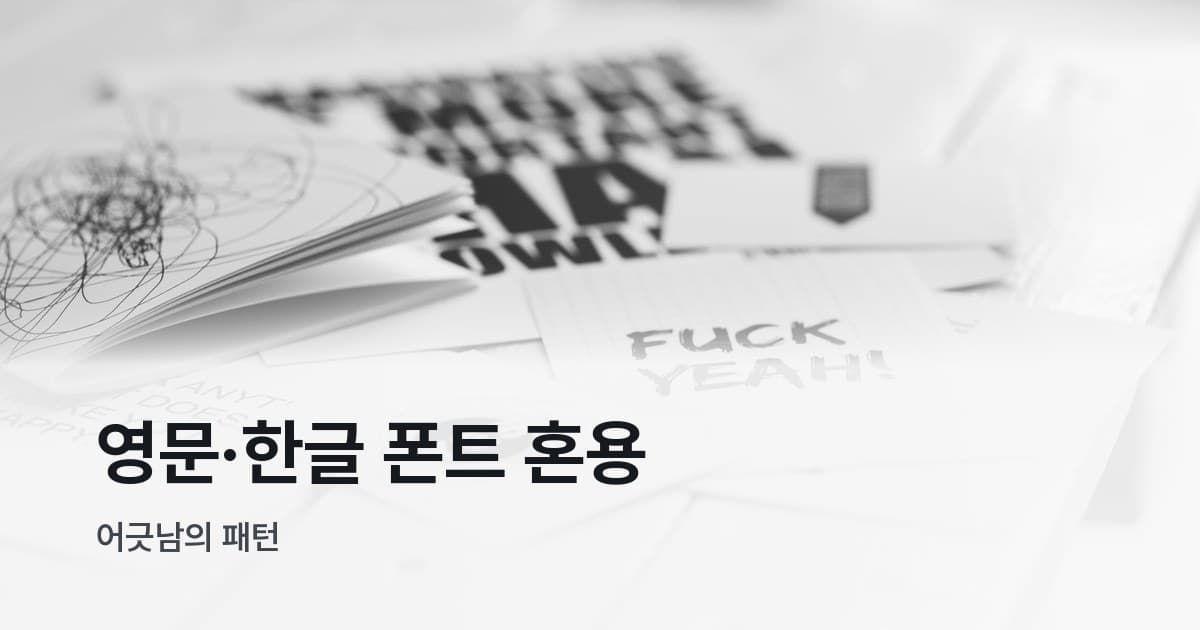
디자인 파일을 열어두고 한 시간째 폰트 조합을 바꿔보는 상황을 한 번쯤 겪어봤을 거예요. 영문 폰트도 예쁘고, 한글 폰트도 마음에 드는데 — 막상 둘을 나란히 놓으면 뭔가 엇나간 느낌. 크기를 올려봐도, 자간을 조정해봐도 여전히 찜찜하다. 결국 시간에 쫓겨 "그냥 Noto Sans로 퉁치자"고 타협했다면, 그 실패는 감각 부족 때문이 아니에요.
어색한 결과물에서 거꾸로 올라가 보면, 원인은 거의 세 가지 중 하나에 걸립니다. x-height 불일치, 굵기 밀도 미스매치, 그리고 분위기 충돌. 이 글은 "잘 어울리는 조합 목록"을 나열하는 대신 — 실제로 무너지는 지점부터 먼저 짚고, 그 원인을 거꾸로 설명합니다. 실패가 어디서 오는지 알면 처음 보는 폰트 조합도 스스로 판단할 수 있거든요.
결과물이 어색하다면 x-height 불일치부터 의심하라
x-height는 라틴 소문자 'x'의 높이, 즉 소문자가 실제로 차지하는 세로 공간이에요. 같은 16px라도 x-height가 큰 폰트는 꽉 찬 느낌을 주고, x-height가 낮은 폰트는 같은 크기에서 훨씬 가냘프게 보입니다.
문제는 한글과 영문이 서로 완전히 다른 설계 체계에서 출발한다는 점이에요. 한글은 정사각형에 가까운 고정폭 공간 안에 자모가 배치되는 구조라, 영문 소문자의 어센더·디센더 개념 자체가 없어요. 그래서 두 폰트를 같은 포인트로 나란히 놓으면 높이 기준이 어긋나 — 한글이 지나치게 크거나, 영문이 유독 작아 보이는 현상이 생깁니다.
Pretendard가 Inter와 잘 어울리는 이유가 여기에 있어요. Pretendard는 라틴 글리프를 Inter에서 가져와 한글(본고딕 계열)과 조합해, 같은 환경에서 x-height가 자연스럽게 통일되도록 설계됐거든요. Google Fonts Knowledge에서도 x-height를 서로 다른 폰트를 혼용할 때 시각적 균형에서 가장 먼저 확인해야 할 기준으로 꼽습니다. 반면, x-height가 유독 낮은 클래식 세리프 영문 폰트에 고밀도 한글 폰트를 그냥 붙이면 — 한글이 영문보다 눈에 띄게 크고 무거워 보이는 결과가 나와요.
같은 Regular인데 한글만 더 진해 보이는 굵기 밀도 미스
"둘 다 Regular니까 균형은 맞겠지."
근데 한글 쪽이 확연히 더 어둡게 보이면, 내 모니터가 이상한 걸까요? 아니에요.
한글은 자모 획이 영문 알파벳보다 훨씬 많고, 정사각형 공간 안에 빽빽하게 들어갑니다. 획 굵기 자체는 같아도 페이지 위에서 더 어둡고 조밀하게 느껴질 수밖에 없는 구조예요. 이건 폰트 품질의 문제가 아니라 한글이라는 문자 체계 자체의 특성입니다.
그래서 실무 보정 방향은 간단해요. 영문 Light + 한글 Light 조합에서 한글이 확연히 진해 보인다면, 영문만 Regular로 올리거나 한글 font-weight를 한 단계 내리는 거예요. 반대로 처음부터 이 문제를 피하고 싶다면, 같은 패밀리 안에서 라틴과 CJK를 함께 설계한 폰트를 고르면 됩니다. Noto Sans와 Noto Sans KR이 그 사례예요 — 같은 프로젝트에서 명도를 맞추도록 만들어졌기 때문에 같은 weight로 써도 비교적 잘 맞거든요.
이 문제가 가장 두드러지게 나타나는 조합이 Light·Thin 계열 영문과 Regular 한글을 섞을 때예요. 영문을 가늘게 써서 세련된 느낌을 내려다가, 옆에 붙은 한글이 지나치게 무겁게 보여서 결국 전체적으로 불균형한 결과가 나오는 경우입니다. 이 경우는 한글도 Light로 낮추는 것보다 — 두 폰트 모두 Regular 이상에서 시작하고 무게를 함께 조정하는 편이 더 안정적인 결과를 줘요.
수치는 다 맞는데도 글자가 싸우는 느낌, 분위기 충돌
글자 크기와 굵기 밀도가 잘 맞더라도 분위기가 충돌하면 조합은 깨집니다.
Playfair Display는 획 굵기 대비가 강한 고전 세리프 서체예요. 고급스럽고 우아한 인상을 주는 폰트죠. 여기에 획 굵기가 균일하고 현대적인 Noto Sans KR을 붙이면 — 영문과 한글이 서로 다른 시대에서 온 듯한 이질감이 생겨요. 글자가 싸우는 느낌이랄까요.
Adobe Fonts의 다국어 조판 가이드에서도 감성적 어울림을 먼저 살피고 수치를 나중에 조정하도록 안내합니다. 세리프 영문에는 세리프 한글(본명조, Noto Serif KR)을, 산세리프 영문에는 산세리프 한글(고딕 계열)을 기본으로 가져가는 게 출발점이에요. 세리프·산세리프를 의도적으로 섞는 경우도 있지만, 그건 충분한 크기 대비와 역할 분리(제목용/본문용)가 뒷받침될 때만 성립합니다.
안전한 조합에서 공통점을 역산하면
아래는 영문 폰트와 한글 폰트의 조합을 x-height·굵기·분위기 세 기준에서 왜 어울리는지 정리한 것입니다. 목록보다 근거 쪽에 주목해 보세요 — 이 표의 진짜 목적은 조합 암기가 아니라, "왜 되는지"를 역산하는 데 있어요.
| 영문 폰트 | 한글 폰트 | 어울리는 근거 |
|---|---|---|
| Inter | Pretendard | Pretendard가 Inter의 라틴 글리프를 가져와 한글과 조합 — 같은 환경에서 x-height 자연 통일 |
| Noto Sans | Noto Sans KR | 같은 Noto 프로젝트에서 라틴·CJK 명도 통일 설계 |
| Playfair Display | 본명조 (Source Han Serif) | 획 대비 있는 세리프 계열 — 분위기 일치 |
| Georgia | Noto Serif KR | 중간 세리프 명조 계열 — 웹 가독성·분위기 일치 |
| Roboto | Noto Sans KR | Google 산하 산세리프 계열 — 굵기·간격 기준 정렬 |
이 표에서 공통점을 역산하면 세 가지예요. 같은 프로젝트에서 함께 설계됐거나, 같은 세리프/산세리프 계열이거나, 수직 메트릭을 참고해 맞추도록 만들어진 경우. 이 세 조건 중 하나라도 해당하면 일단 안전한 조합이에요.
어색함이 느껴졌을 때 어디서 무너졌는지 역산하는 법 🔍
"이미 써봤는데 어색해" — 이 상태에서 시작하는 역산 흐름입니다. 위에서 짚은 세 가지 실패 원인을 기준으로, 느껴지는 증상에서 거꾸로 올라가면 원인을 찾을 수 있어요.
증상: 한글과 영문의 시각적 크기가 다르게 느껴진다
포인트는 같게 설정했는데도 한글이 유독 크거나 영문이 왜소해 보인다면 x-height 문제예요. 두 폰트를 같은 크기로 나란히 놓고 라틴 소문자 높이를 기준으로 비교해 보세요. 차이가 눈에 띄게 크다면 — 폰트 자체를 바꾸거나, 시각적으로 작아 보일 수 있어 한글 쪽 font-size를 살짝 낮추는 경우도 있습니다. Pretendard + Inter처럼 수직 메트릭을 맞춰 설계된 쌍을 쓰면 이 문제 자체가 발생하지 않아요.
증상: 한글만 확연히 어두워 보인다 (같은 Regular인데)
이건 앞서 패턴 2에서 짚은 구조적 특성이에요 — 틀린 감각이 아닙니다. 한글 자모의 획 수와 밀도가 영문 알파벳보다 훨씬 높아서, 같은 weight라도 페이지 위에서 더 어둡게 느껴집니다. 보정 방향은 간단해요. 영문을 Light에서 Regular로 한 단계 올리거나, 한글 font-weight를 한 단계 낮추면 됩니다. 처음부터 피하고 싶다면, Noto Sans + Noto Sans KR처럼 같은 프로젝트에서 명도를 함께 맞춰 설계된 쌍을 선택하는 게 근본 해결책이에요.
증상: 수치는 맞는 것 같은데도 두 폰트가 따로 놀아 보인다
세리프·산세리프 계열 불일치, 또는 시대적 감성 충돌을 먼저 의심하세요. Playfair Display처럼 클래식 세리프 영문에 현대 산세리프 한글을 붙이면 수치가 아무리 맞아도 글자가 싸웁니다. 세리프 영문이라면 한글도 세리프 계열(본명조, Noto Serif KR)로, 산세리프 영문이라면 한글도 고딕 계열로 가져가는 게 출발점이에요. 일부러 섞는 경우라면 제목과 본문 역할을 분리하고 크기 대비를 충분히 줘야 성립합니다.
마지막: 미리보기에서는 좋아 보이는데 실제 레이아웃에선 이상하다
폰트 미리보기 페이지는 단일 텍스트를 최적 환경에서 보여줍니다. 실제 레이아웃은 달라요. 제목과 본문이 함께 있는 실제 텍스트 블록을 렌더링해서 확인하고, 가능하면 화면 해상도를 낮춰서도 봐야 해요. 고해상도에서만 좋아 보이는 조합은 실사용에서 뭉개질 수 있습니다.
실패를 줄이는 출발점, 폰트 성격부터 파악하기
세 가지 실패 패턴을 뜯어보면 같은 질문이 나와요. 처음에 폰트 두 개를 나란히 놓기 전에 — 설계 배경과 계열을 먼저 파악했느냐는 것. Noto 패밀리나 Pretendard + Inter처럼 처음부터 함께 설계된 쌍은 x-height와 굵기 밀도 문제 자체를 피하고 시작할 수 있어요. 그 범위 안에서 시작하면 수치 보정에 쓸 에너지를 다른 데 쓸 수 있죠.
수치가 안 맞을 때는 보정할 수 있고, 계열이 다를 때는 대체 폰트를 찾으면 돼요. 그런데 "왜 어색한지" 모른 채로 계속 바꾸면 운 좋게 맞는 조합을 찾아도 다음번엔 또 처음부터예요. 실패 원인을 한 번 역산해두면, 그 다음 작업부터는 훨씬 빠르게 판단할 수 있습니다.